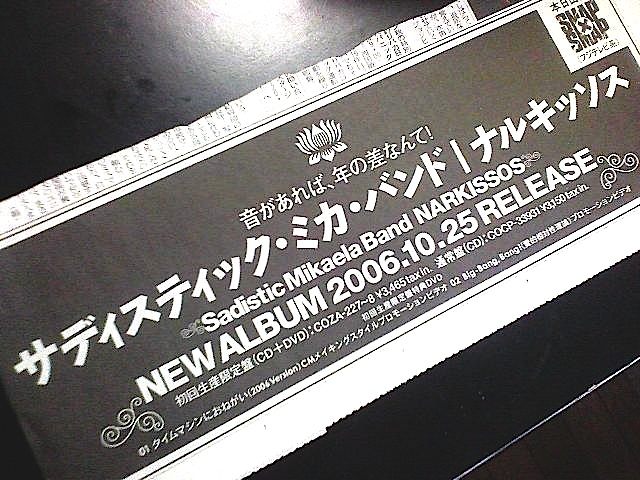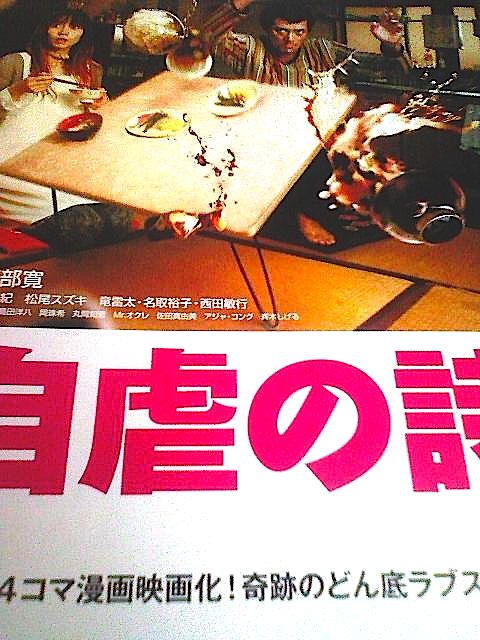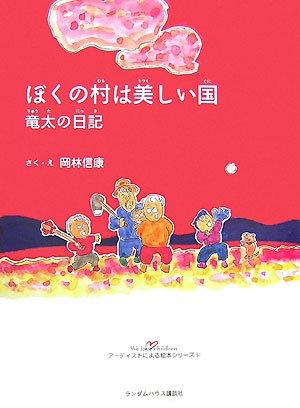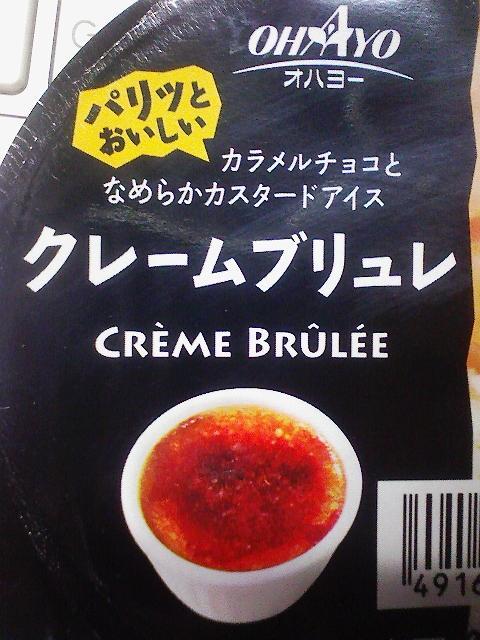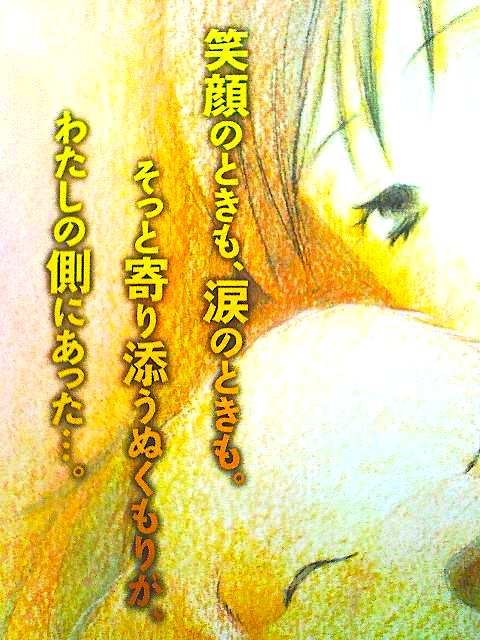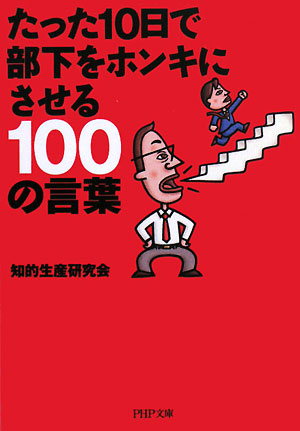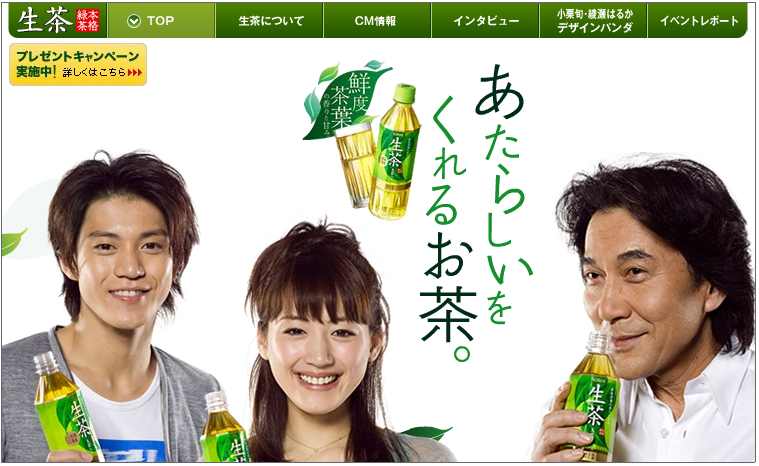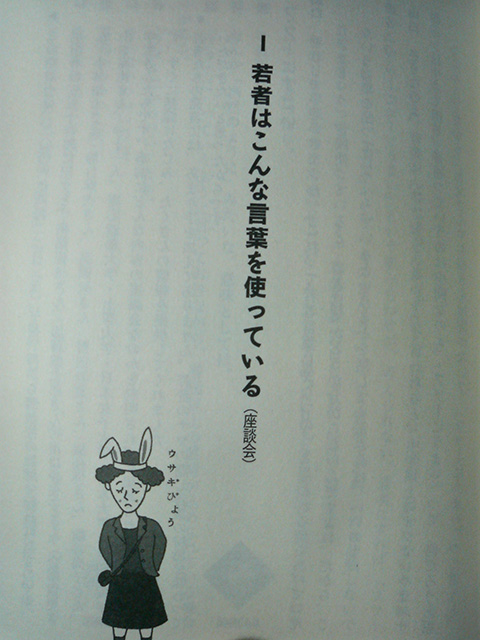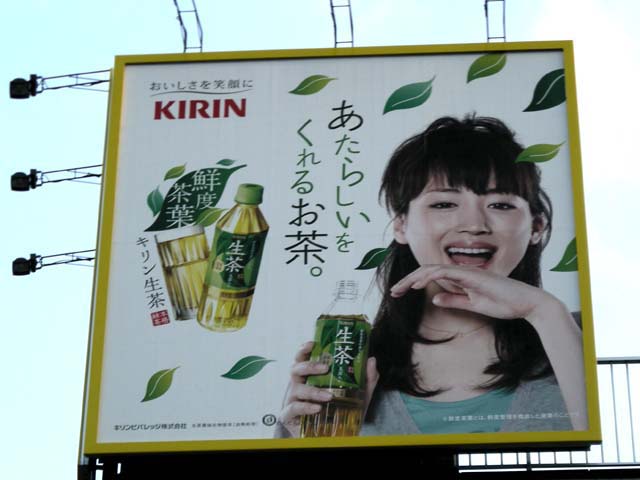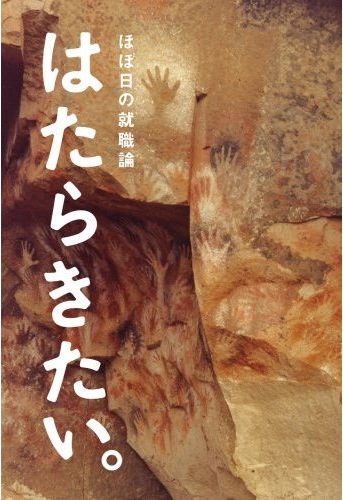
料理本の表紙 さとうゆたか
書名:定番おかずをもっと安く!もっとおいしく!
(別冊すてきな奥さん)
発行:主婦と生活社
本の題名 さとうゆたか
書名:ライオンのクリスチャン
アンソニー・バーク(著)
ジョン・レンダル(著)
西竹 徹(訳)
鍋料理の本 さとうゆたか
本文ページの見出しにも、たくさん使われているようだ。
書名:はじめてのル・クルーゼ
著者:黒川愉子
発行:河出書房新社
訃報 さとうゆたか
フジテレビ元プロデューサーの横沢彪氏が、8日に亡くなったそうだ。
書 名:テレビの笑いを変えた男 横澤彪かく語りき
著 者:横澤彪
聞き手:塚越孝
発 行:扶桑社
PR誌の表紙 さとうゆたか
書名:asta*(アスタ)
発行:ポプラ社
漫画のセリフ さとうゆたか
BE-LOVEという漫画雑誌に連載されている
深見じゅんの「みみっく」という作品。
どれを食べるか、なかなか決まらん。 さとうゆたか
高知の観光広告ですね。
数日前の新聞で。
本の表紙 さとうゆたか
書名:アイシテル~海容 前編 (1)
作者:伊藤実
発行:講談社
カタカナの画線が細い直線で繋がれ、ちょっと不思議な雰囲気が出ています。
こちらは後編です。
雑誌連載の扉ページ。
表紙 さとうゆたか
このぐらい大きく使われると気持ちイイ。
書名:でらつれ
著者:小沢一敬
発行:講談社
本の表紙 さとうゆたか
書名:今さら聞けない地デジの疑問
発行:インフォレスト